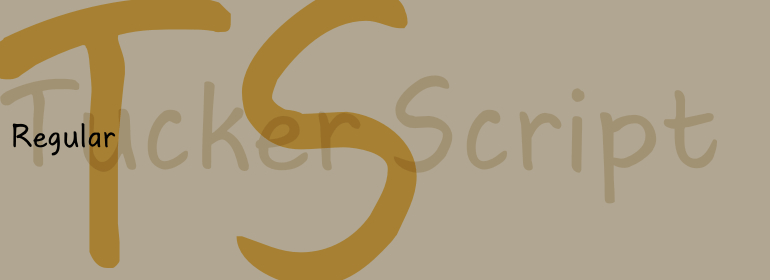
Tucker Script™
Tucker Script™,这款字体结构工整、笔画清晰,兼顾美观与易读性,适用于标题、正文、海报、包装、LOGO 等多种场景。字形优雅稳定,风格百搭耐看,适配日常排版与创意设计,让文字呈现更舒适、更具质感。Tucker Script™一笔一画,皆是细节,以均衡的比例、流畅的线条打造舒适视觉体验,字形端正大气,风格简约现代。无论是商业设计、品牌宣传还是日常排版,都能轻松驾驭,让文字更有格调与力量。Tucker Script™字体下载。